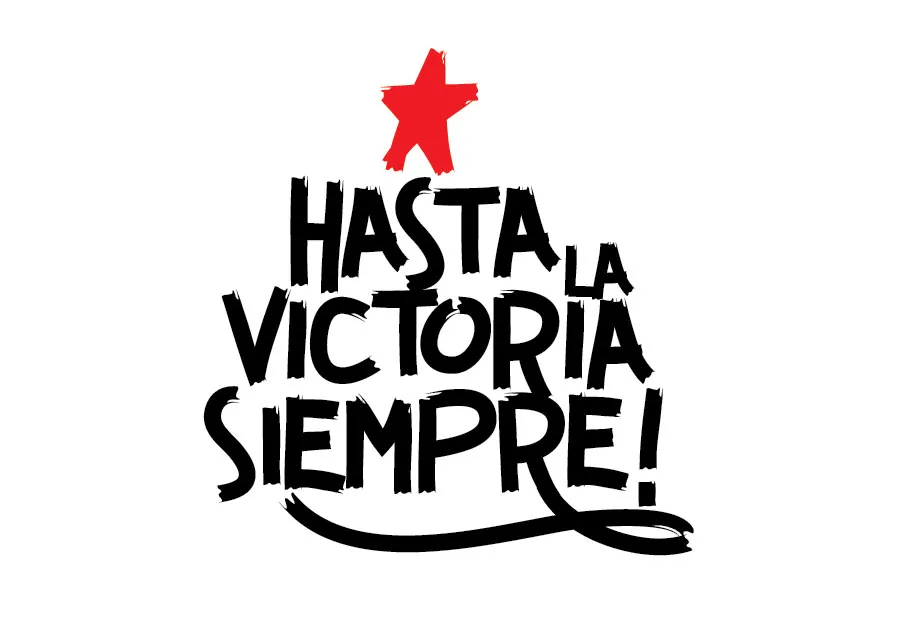
A Guerrilla Font é uma tipografia inspirada nos grafites subversivos, criada como uma simples reflexão poética sobre o lazer. Esta fonte livre é perfeitamente adequada para diversas aplicações visuais, desde a criação de marcas e embalagens até desenhos de capa de álbum e panfletos. A inspiração desta fonte vem dos grafites urbanos que têm sido uma poderosa ferramenta para expressar pensamentos independentes e criticarem o status quo. Ela reflete não apenas a natureza libertária desses sinais visuais, mas também seu impacto na cultura popular e nas comunidades locais. Esta fonte é ideal para qualquer aplicação visual que valorize uma mensagem forte e original. Suas linhas leves e dinâmicas combinam perfeitamente com uma variedade de estilos e formatos. Seja você designer, publicitário ou artista gráfico, a Guerrilla Font oferece um poderoso canal para expressar suas ideias através do design visual. Com sua simplicidade e versatilidade, essa fonte não apenas preenche o seu portfolio com uma nova opção de estilo, mas também permite que você utilize sua criatividade para criar designs memoráveis. Não importa se está trabalhando em um projeto para marcas digitais ou capas de discos vinil, a Guerrilla Font tem o poder de reforçar sua marca e impacto visual.